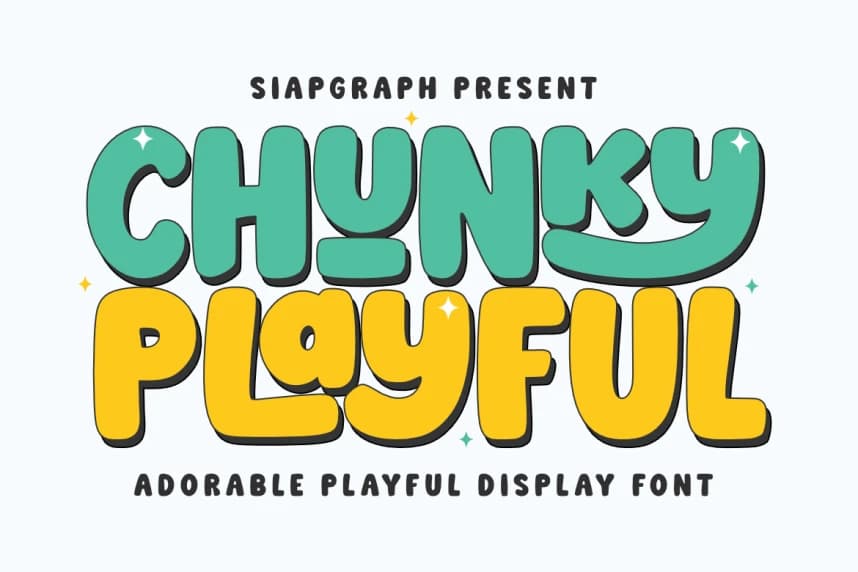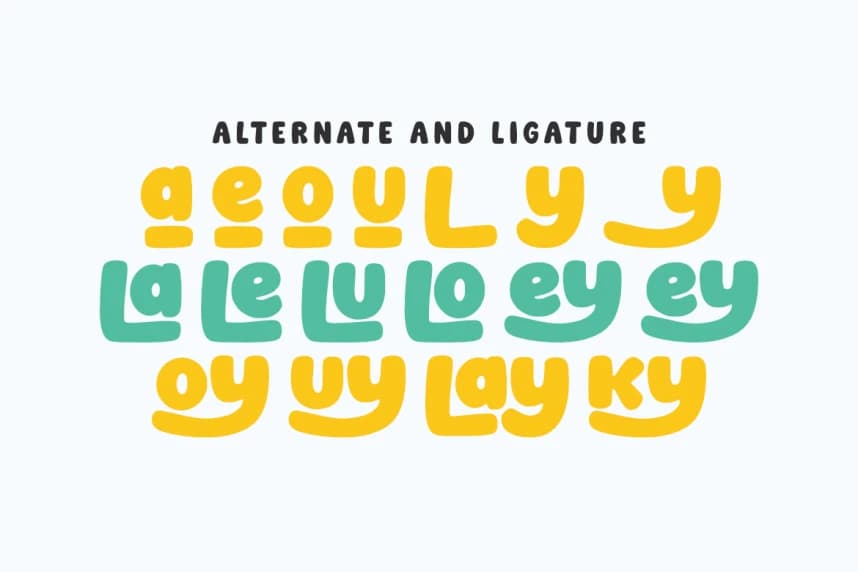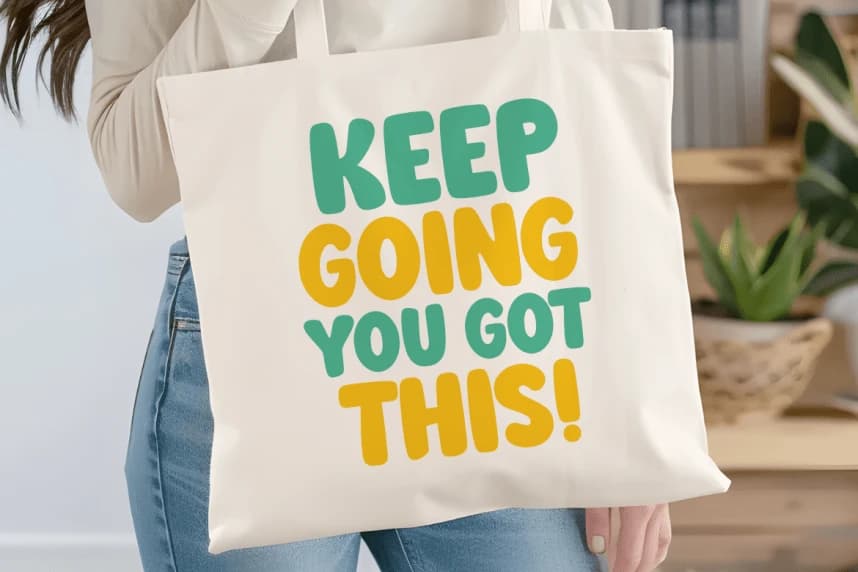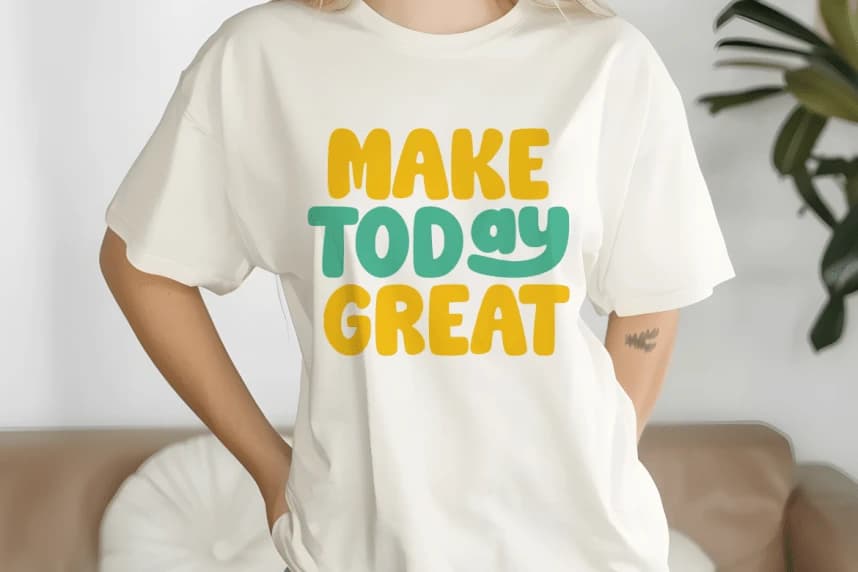
Chunky Playful Font
Chunky Playful Font, retro pop kültürünün yumuşak, yuvarlak hatlarından ve neşeli çocukluk atıştırmalıklarından ilham alan sevimli, köpüklü bir gösteri yazı tipidir. Bu yazı tipi, kalın, belirgin çizgilere ve dostane, enerjik bir kişiliğe sahip olup yaratıcı projenize anında bir sevinç ve sıcaklık h
Chunky Playful Font, retro pop kültürünün yumuşak, yuvarlak şekillerinden ve neşeli çocukluk atıştırmalıklarından ilham alan sevimli, kabarcıklı bir gösterim yazı tipidir. Bu tipografi, kalın ve belirgin hatlar ile dostane, enerjik bir kişiliğe sahiptir ve yaratıcı projelerinize anında neşe ve sıcaklık katmayı amaçlar.